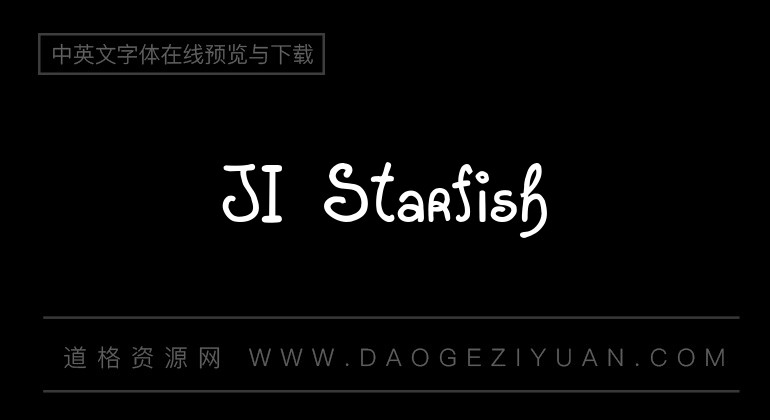
JI Starfish 是一款由 Just in Type 推出的字体,它是一款时尚的抽象字体,具有现代感和灵活性。它的特点是把简洁的线条与抽象的形状结合在一起,形成一种独特的字体风格。它可以用于各种商业和个人项目,如广告、海报、书籍封面、海报、标识和标志等。内容介绍
JI Starfish是一款非常不错的手写艺术字体,具有很好的视觉感,适合于文化类的宣传设计、商业类品牌的广告和产品包装设计以及个性化文字排版等较多场景。